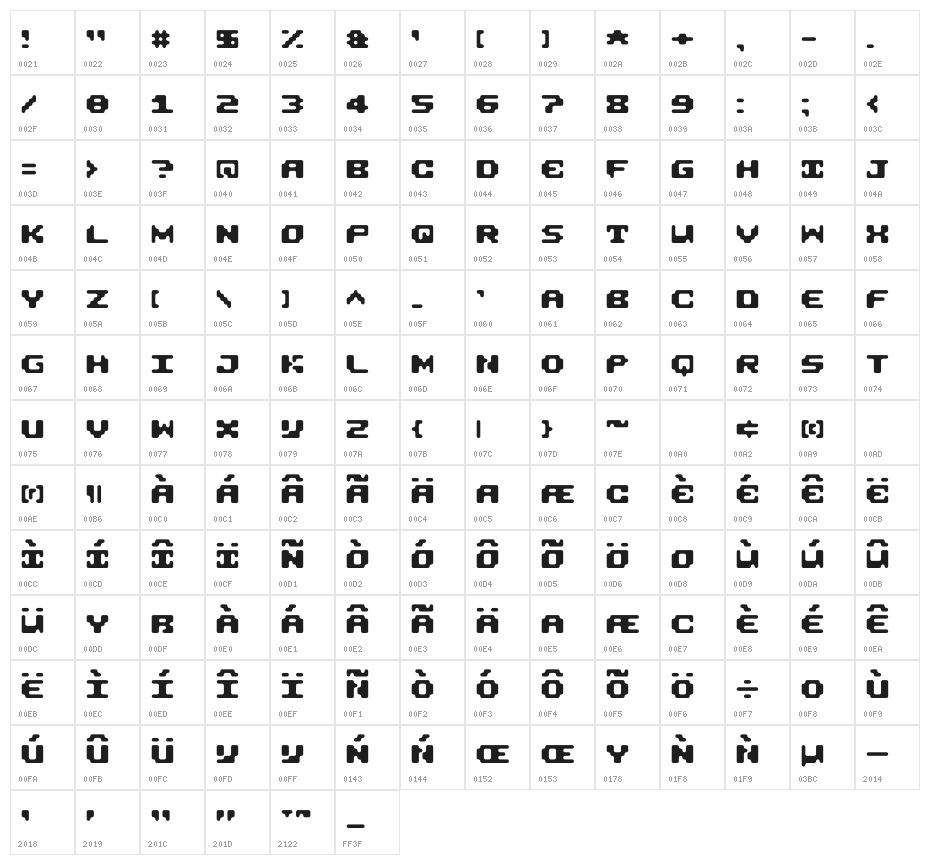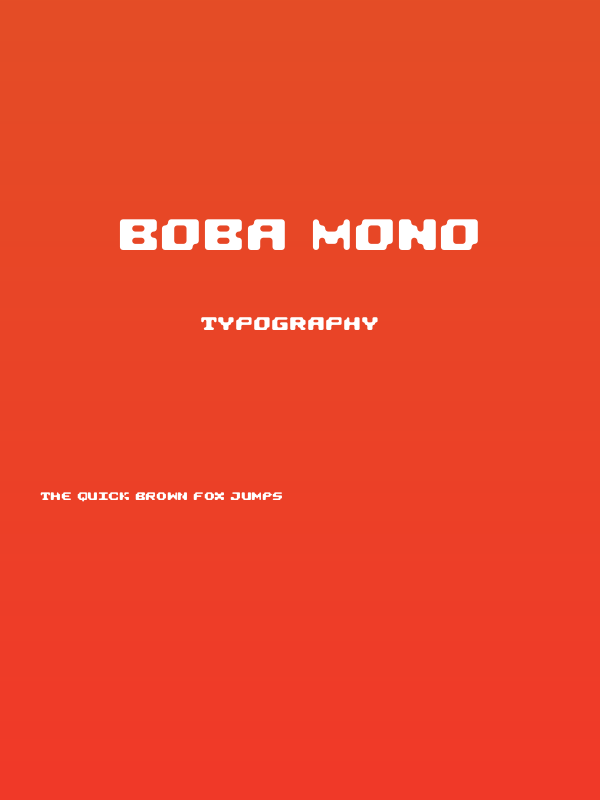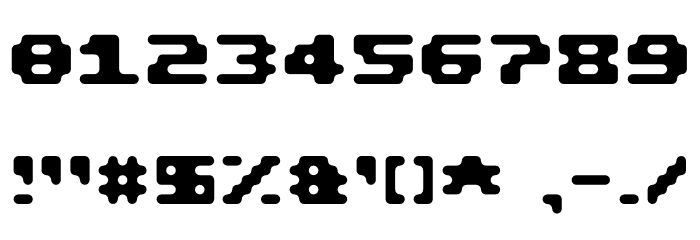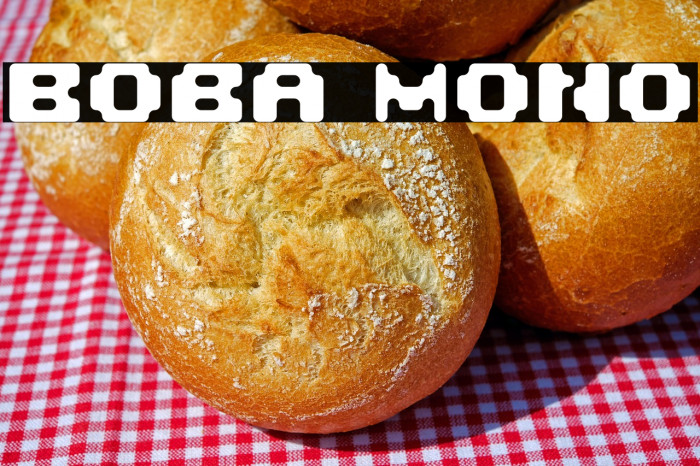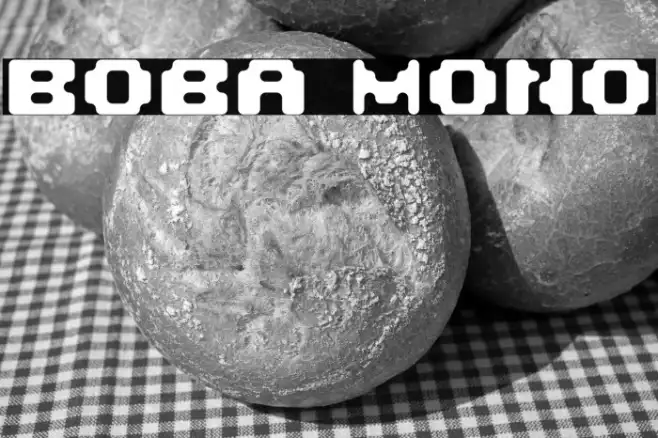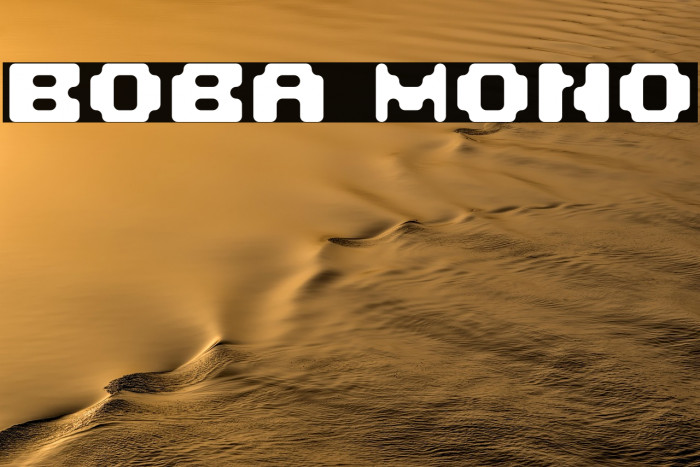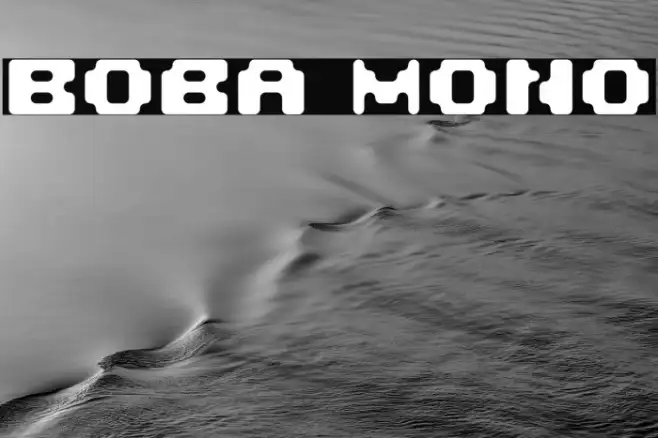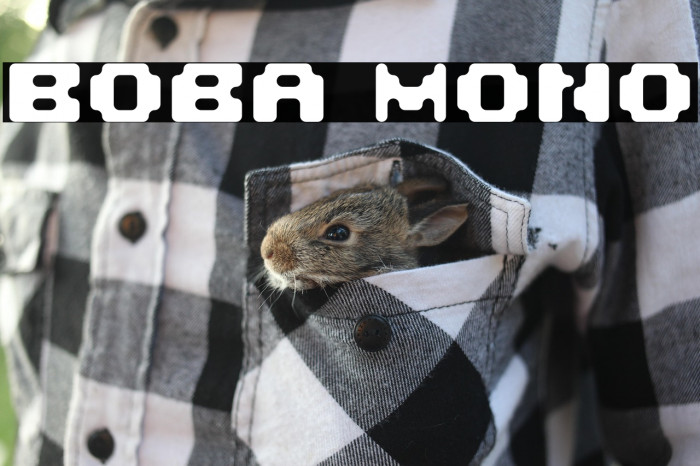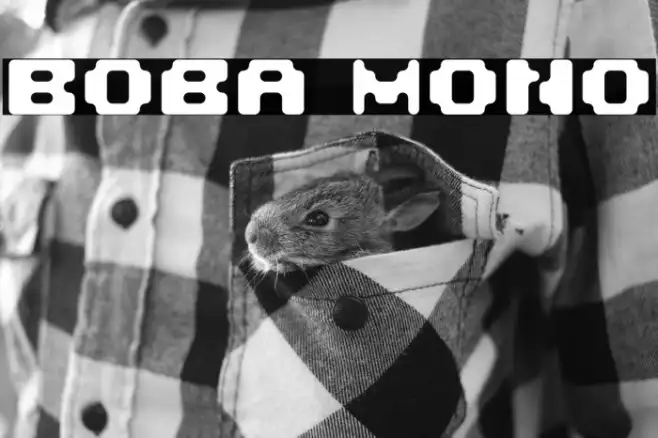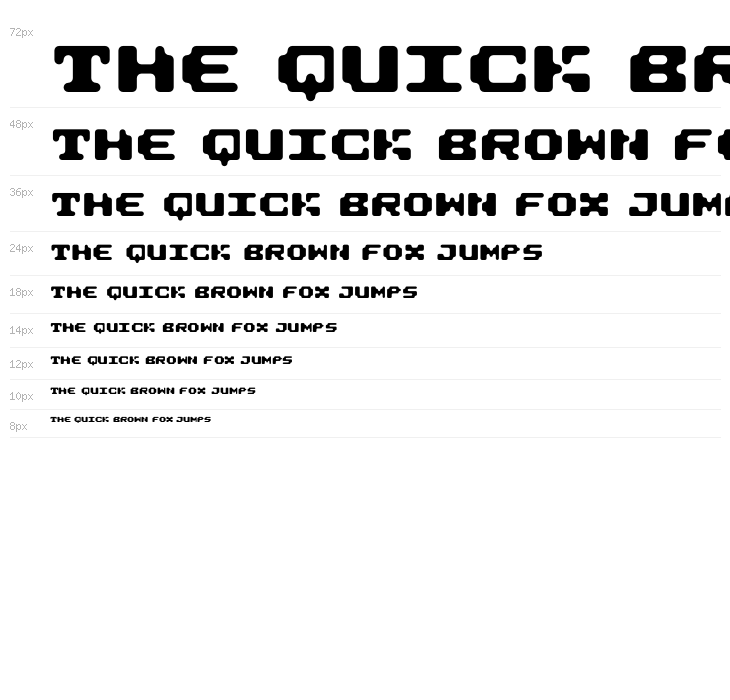
Boba Mono Font
| Anwendungsfall | Logos, Headlines, Posters |
| Vorgeschlagene Projekte | Ideal for tech-themed designs, modern branding, playful posters, and digital interfaces. |